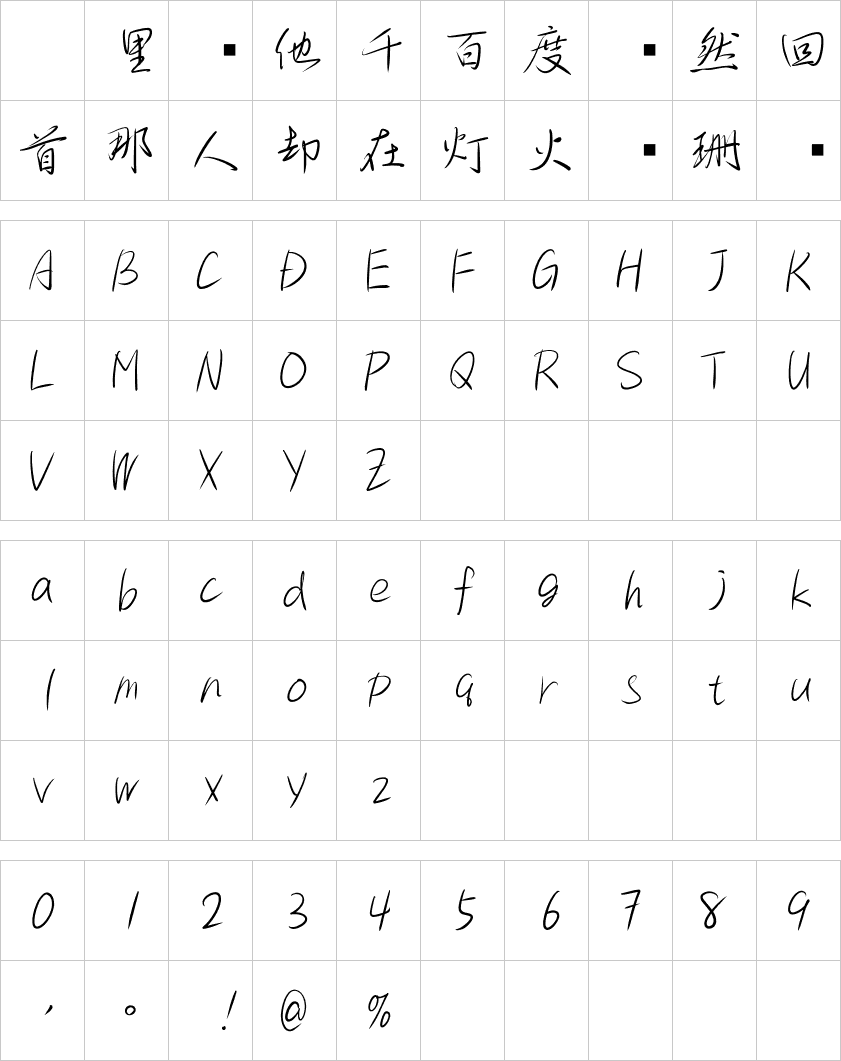
しょかきさらり行体
【しょかきさらり(行体)】 ・僕がちまちま書いていたフォントを公開することにしました。 ・表示できる文字はJIS第一水準の漢字までです。罫線文字など一部記号は表示できません。(このフォントが好評でしたら、第二水準を進める気力が出るかもしれません) ・無料で使えます。(下記利用規約をお読みください) ・すらすら流れるような筆致の字を目指しました。 ・長い間書いていると、字の巧拙・大小・筆致などが安定しません。一部は書き直したのですが、不揃いな字があると思います。 ・字体・字形は好みのものを使っています。 ・「行体」と銘打っていますが草書の形を使っているものもあります。 ・なお、本ファイルは武蔵システム(https://opentype.jp/)のTTEditを使って作成しました。 ・あ、あと、言いたいことなんですが、フォント掲載する際に、「毛筆系」に分類してあることが多いのですが、筆圧検知のペンタブで書いた字って毛筆系なのか?と思うことがあります。(いったい何系なのだろうか)